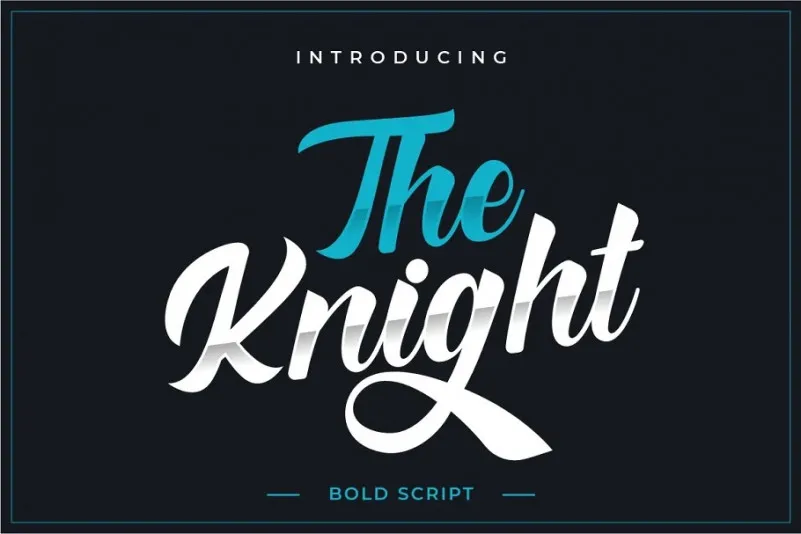
The Knight Font – Download Grátis
Aqui está a descrição solicitada para a página de download da font ‘The Knight Font’, com o estilo informado e convencional: O The Knight Font é uma nova variante de um tipo de letra feita à mão, que combina os traços elegantes das letras cursivas com características modernas. Criada pela PutraCetol Studio, esta fonte foi inspirada nas títulos de jornais e panfletos, bem como nos estilos de escrita em letras estilizadas do streetwear. Com um design marcante e atemporal, o The Knight Font é perfeito para criações visuais que exigem uma aparição moderna. Seja você criando elementos de marca ou trabalhando em designs digitais, este fonte é um ótimo opção. Suas linhas robustas e levemente arredondadas permitem que seu design brilhe com um toque de elegância no meio da tendência mais atual. Essa font se destaca como uma alternativa perfeita para quem busca algo além do básico, mas ainda precisa de uma solução de layout forte e resistente. Afinal de contas, The Knight é a escolha certa para qualquer designer que deseja dar um toque único e moderno em seus projetos.